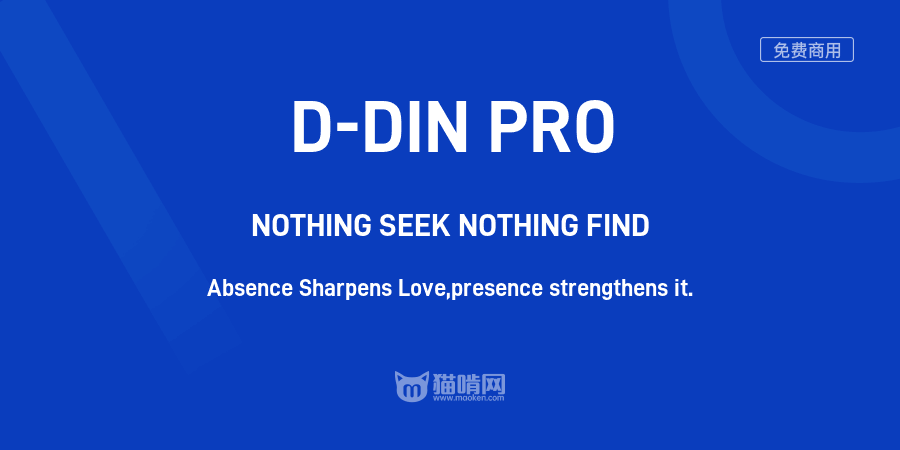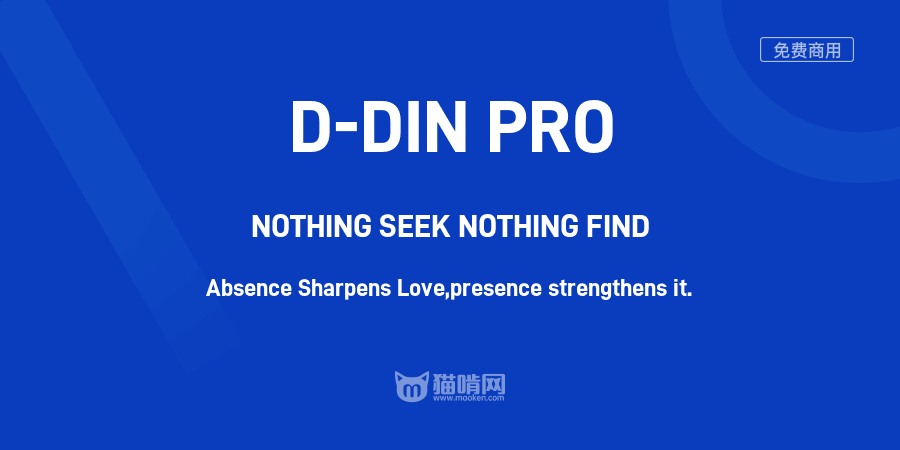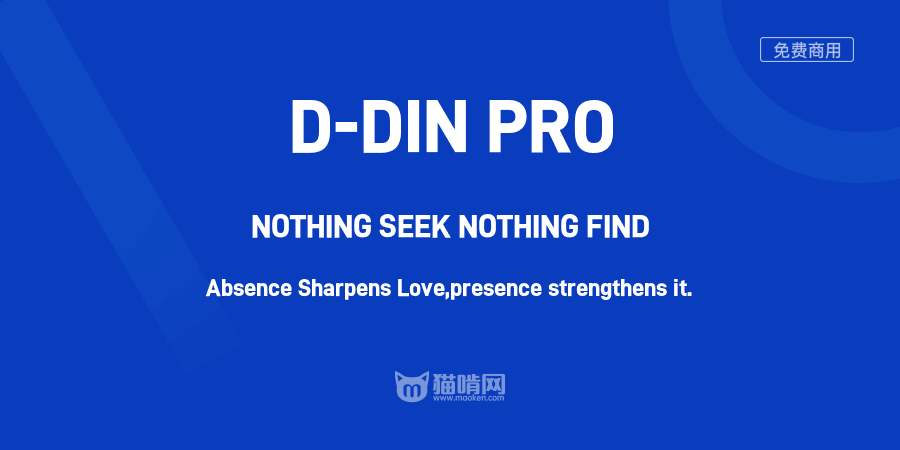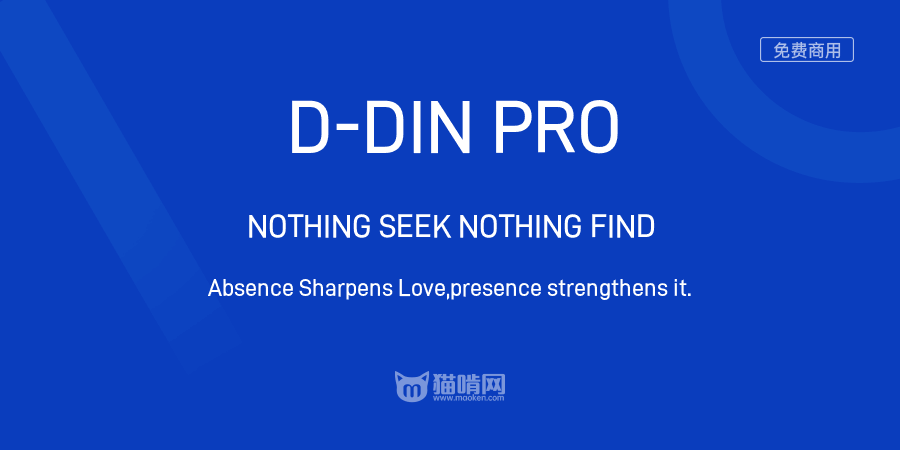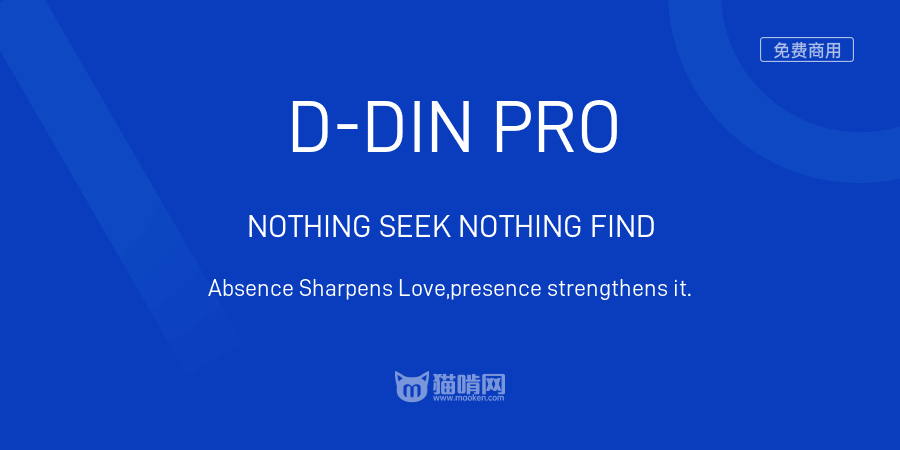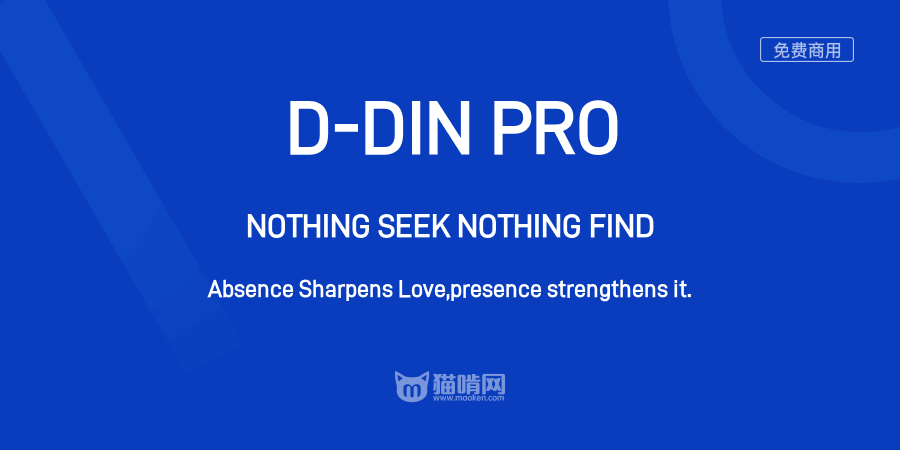
D-DIN PRO
字体作者:datto (外国) 字体字重:6个
字体介绍
D-DIN PRO字体是由Adrian Frutiger于1997年设计的无衬线字体。它是DIN字体家族的现代诠释,最初是为1930年代的德国路标设计的。
它是一种多用途字体,可用于印刷、网络和移动设备等各种用途。
这款经典的类DIN设计现代化的必备字体现在包括从Regular到Heavy的六种字重。
D-DIN PRO是一种平衡和易读的字体,既现代又永恒。它是各种项目的不错选择,并且为任何设计增添一丝优雅是安全的。
由于其简洁的字母设计,这种现代字体非常适合用于社交媒体帖子设计、墙壁壁画设计、粗体标题设计以及各种惊艳的文字设计。这种奇妙的字体还适合制作动态标志设计、海报设计等等。
您可以利用这个吸引人的字体进行各种名称设计、标识、图像布局、壁纸设计以及惊艳的家居装饰用途。如果您想要制作令人印象深刻的文本设计、发票设计、文档用途、标题设计以及产品包装设计。
什么是D-DIN PRO字体?
D-DIN PRO字体是一种现代的无衬线字体。这种字体以其干净简洁的设计风格而闻名,使其易于阅读。
我可以在哪里使用D-DIN PRO字体?
您可以在各种设计项目中使用D-DIN PRO字体,如网站、标志、海报和文件。它多才多艺,在印刷和数字媒体中都能很好地发挥作用。
• DIN并不是指某一款字体。DIN是Deutsches Institut für Normung(德国标准化学会)的缩写。在1920年代,该机构开始规范化德国的标志和字体,以提高工程和技术文件的一致性和可读性。
DIN字体版本和变体:
DIN 1451 (1931年,设计师:Ludwig Goller )
DIN Engschrift(1992年,出品:Adobe公司)
FF DIN (1995年,设计师:Albert-Jan Pool)
DIN Next (2009年,设计师:小林章)
很好用的字体,直接替代DIN的数字